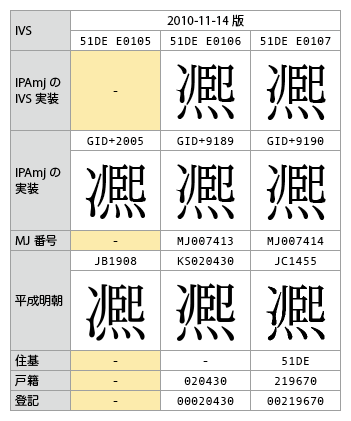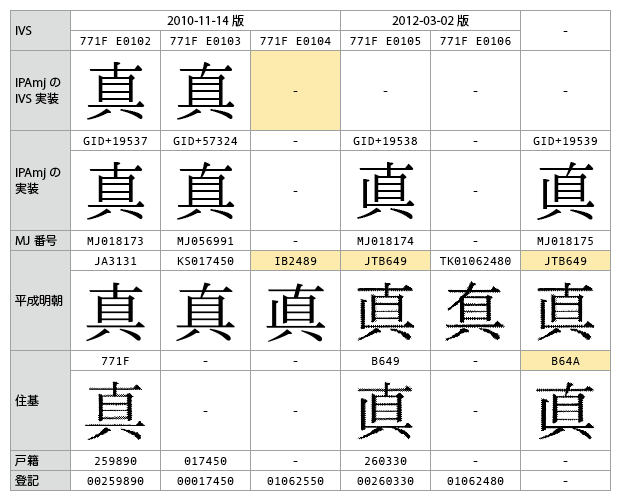
IPAmj明朝がサポートしていないIVS
- IPAmj明朝はHanyo-Denshiの2010-11-14版のIVDをサポートしているが、表示できないIVSが2つ存在する。以下、どういう事情でこうなっているのかについてメモ。
- 表示できないIVSの1つ目は、「凞」を基底文字とする「51DE E0105」(JB1908)。
- 汎用電子は、戸籍統一文字、住基ネット統一文字、登記統一文字を対象とするプロジェクトであり、平成明朝のJB1908(「冫」が下までくる形)はそのいずれにも含まれないため、汎用電子12分冊の文字表に掲載されていない。
- しかし、JB1908は補助漢字グリフ(つまり、ISO/IEC 10646に掲載されているグリフ)であるため、Hanyo-DenshiのIVDを登録する際、特例として追加されたようだ*1。
- そのようなわけで、JB1908は「Hanyo-DenshiのIVDには含まれるが汎用電子の文字表には掲載されていない字」となり、汎用電子の文字表をベースとした文字情報基盤の文字情報一覧表にも含まれていない(MJ番号も振られていない)。
- IPAmj明朝は、このJB1908相当のグリフを持っている(GID+2005)。が、IVSのテーブルは文字情報一覧表に従っているため、そこに存在しない文字のIVSはサポートしないということだと思われる。
- 単純に文字情報一覧表にJB1908を追加してMJ番号を振って「51DE E0105」をサポートすればいいんじゃないのと思わないでもないが、Hanyo-Denshiの2010-11-14版のIVDをフルサポートすることより、「文字情報一覧表には戸籍統一文字と住基ネット統一文字のみを掲載する」というルールのほうが優先順位が高いということだろうか。
- 表示できないIVSの2つ目は、「真」を基底文字とする「771F E0104」(IB2489)。
- こちらの例では、IPAmj明朝はIB2489のグリフを持っていないので、当然、表示しようがない。
- むしろわかりにくいのは、なぜIB2489が2010-11-14版のIVDに含まれているのかという点。Hanyo-DenshiのIVDの最初の登録は、戸籍統一文字と住基ネット統一文字が対象だったが、IB2489はそのどちらでもないからだ。
- おそらく、IVDに登録したかったのは、住基ネット統一文字のB64A(2画目が斜めの形)だったのではないか。しかし、IVDの登録に用いた平成明朝は、住基B64Aを表現できるグリフを持っていない(住基B649と区別できない)。そこでJTB649(住基B649)とは別にIB2489を(住基B64Aのために)登録したのだろうと思う。
- つまり、住基B649(MJ018175)はIVDに登録され損って宙に浮いているとも考えられるわけだが、それで困ったことになるシーンが存在するのかどうかは、よくわからない。